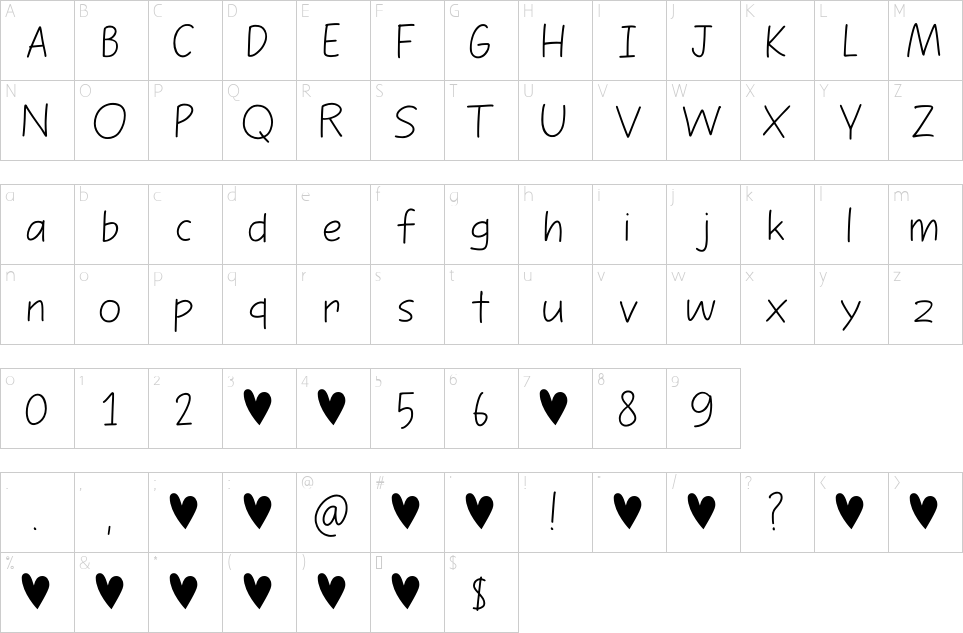
Descubra a encantadora ‘Absolutely Lovely Font’, perfeita para aqueles que buscam uma elegância natural em seus projetos digitais. Desenvolvida por Hanoded, esta fonte apresenta um estilo harmonioso e suave que encaixa-se perfeitamente com textos de design gráfico e escrita criativa. Com uma aparência atraente e versátil, ‘Absolutely Lovely Font’ se adapta facilmente a diversas necessidades de projeto. Seja para criar materiais educacionais, personalizar sua página web ou apenas adicionar um toque especial aos seus documentos pessoais, esta fonte oferece os recursos certos. Com mais de 189 downloads desde seu lançamento, ‘Absolutely Lovely Font’ já foi apreciada por uma ampla gama de designers e criativos. Não hesite em explorar o poder desta fonte para enriquecer sua próxima peça de design.